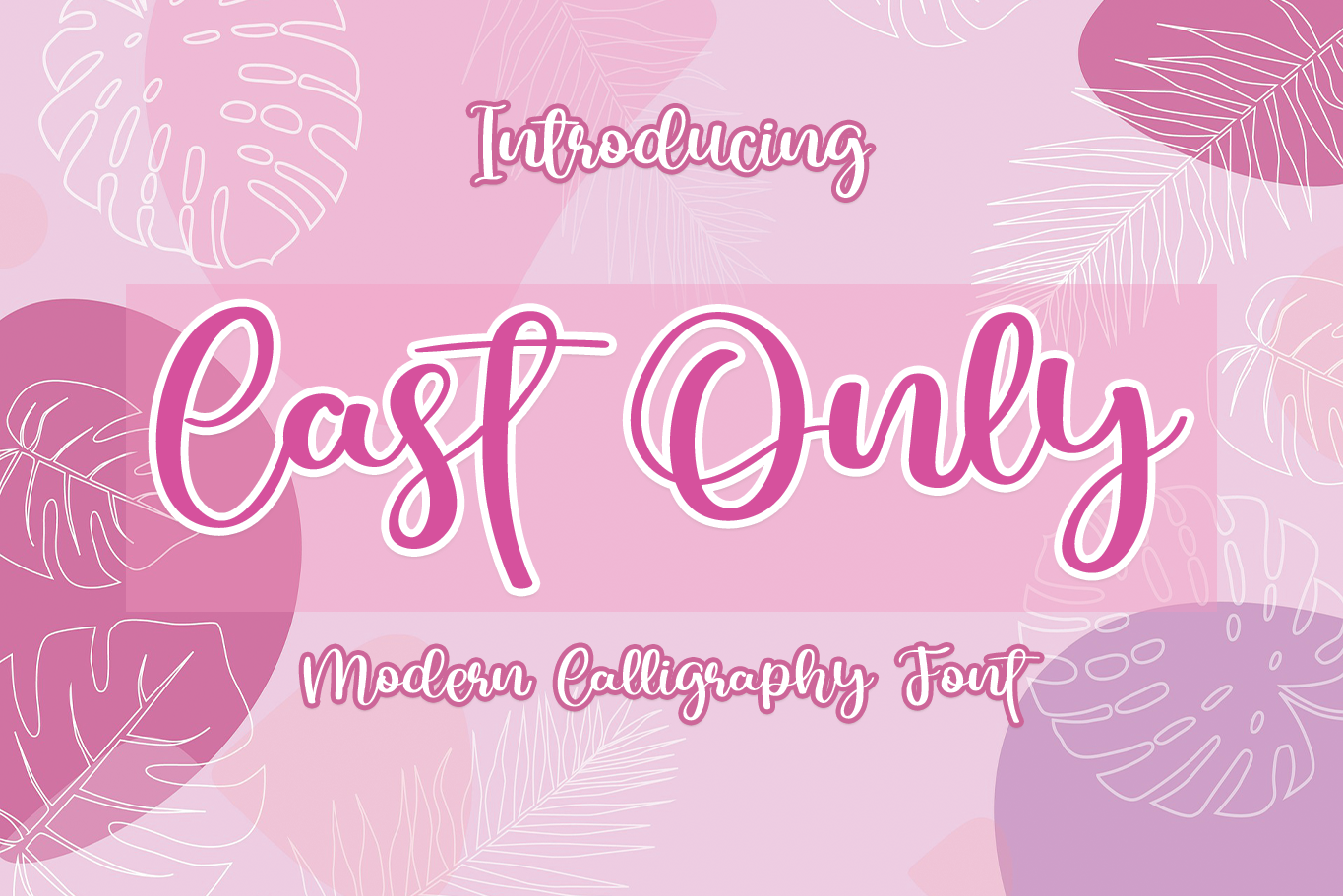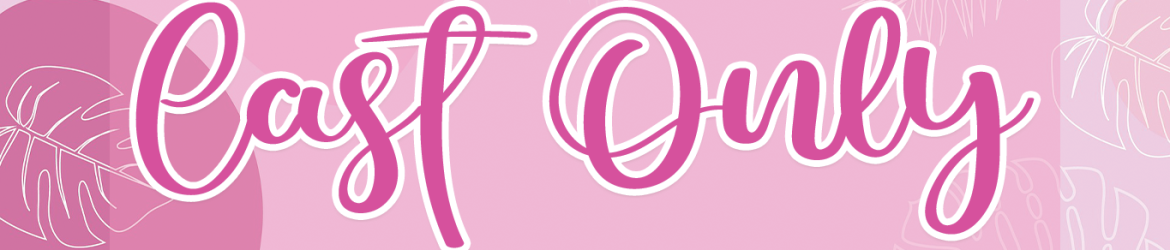
Esta é uma elegante fonte script. Ela foi cuidadosamente construída com detalhes meticulosos. Seja qual seja o tema que você estiver trabalhando, Cast Only certamente se tornará um precioso acréscimo para sua biblioteca de fonts. Com seu potencial para aprimorar qualquer criação, não há dúvida de que esta font é uma excelente adição para seus projetos. Como designer responsável do Erik Studio, nos dedicamos à qualidade e aos detalhes em cada projeto, para garantir que Cast Only seja a escolha perfeita para aqueles buscando um acabamento refinado e versátil para suas fontes de escrita oriental.